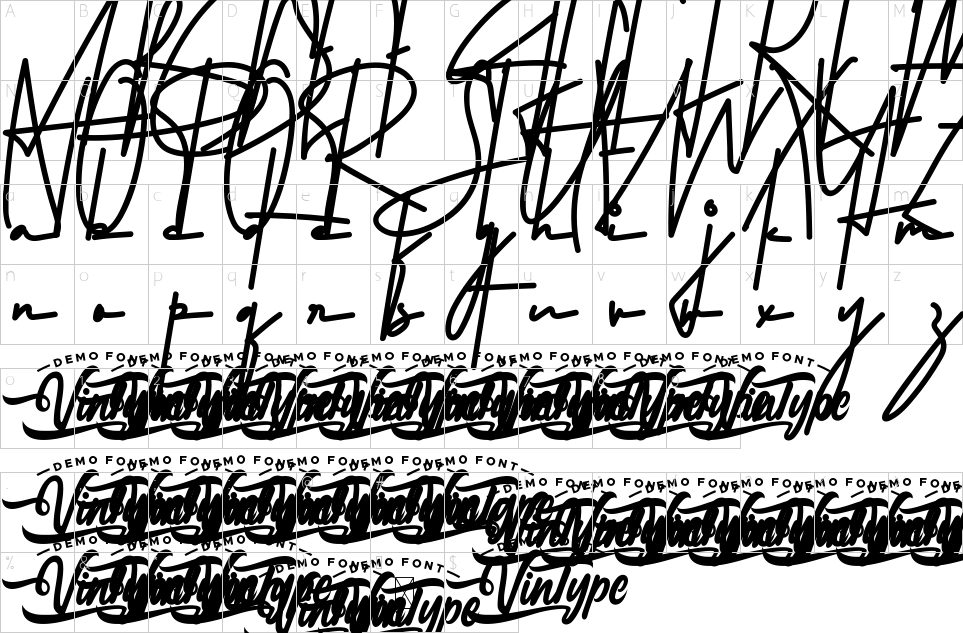
Descubra o After Breakup Font, uma elegante e envolvente fonte para download gratuito, certamente adequada para qualquer projeto gráfico. Desenvolvida pelo designer VinType, esta fonte é ideal para aqueles que buscam uma solução moderna e criativa para seus projetos. Desenvolvida pensando em sua versatilidade, After Breakup oferece uma proposta única e distintiva, capaz de enriquecer qualquer layout. Com 507 downloads já realizados, pode-se dizer que este é um recurso gráfico que se destaca no mercado de fontes gratuitas. Ideal para uso em projetos digitais e impressos, a After Breakup é uma ótima opção para criar um design que realmente chama a atenção. Seja você um designer de web, um profissional de design gráfico ou até mesmo um artista digital, o After Breakup está aqui para fornecer as ferramentas certas para ajudá-lo a criar uma obra de arte inovadora e única.